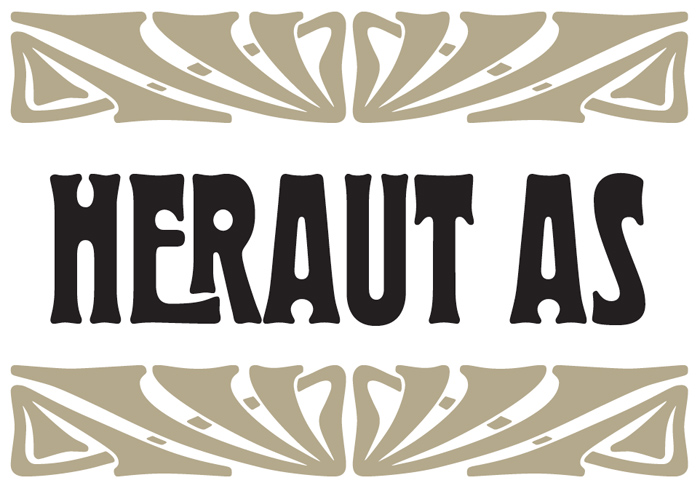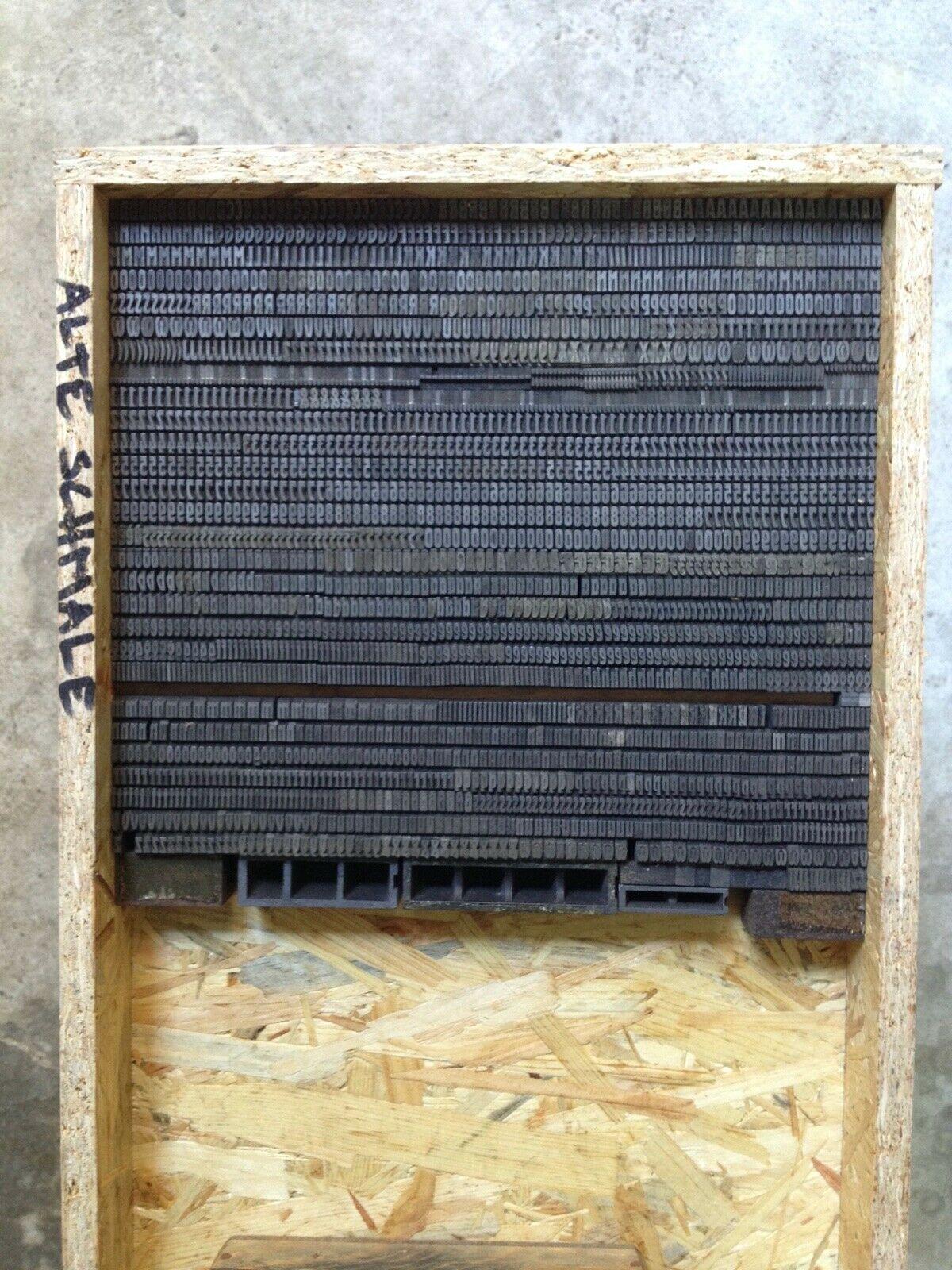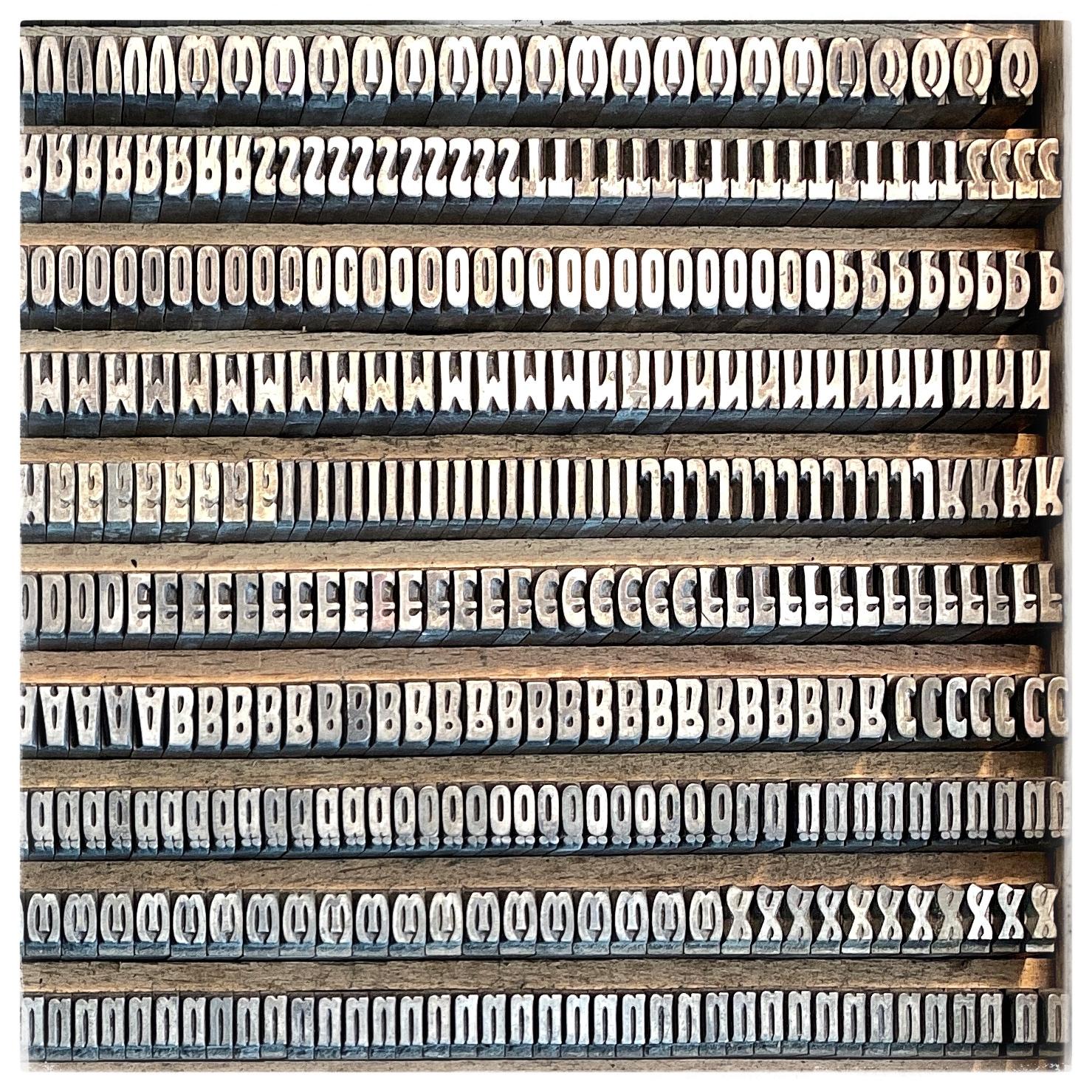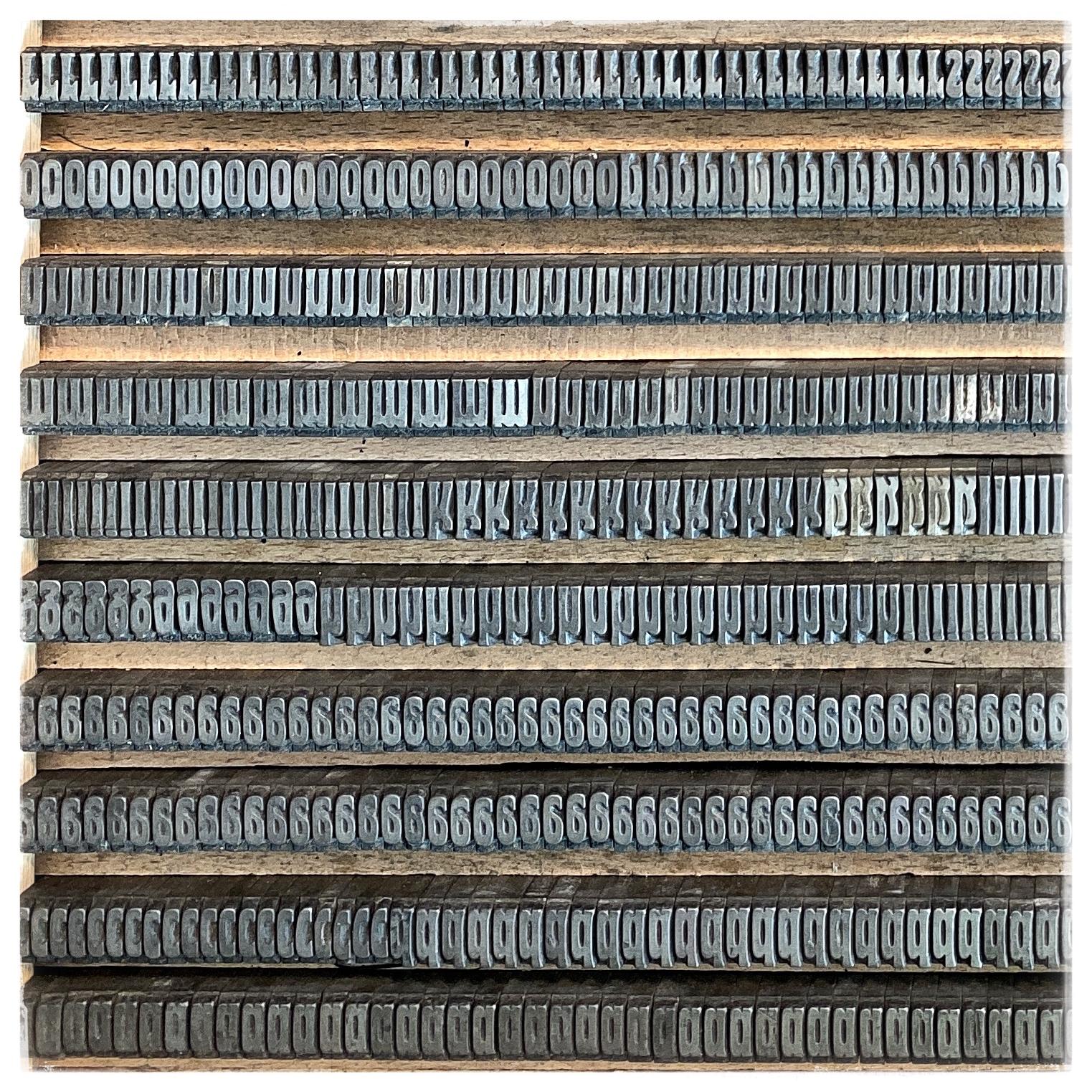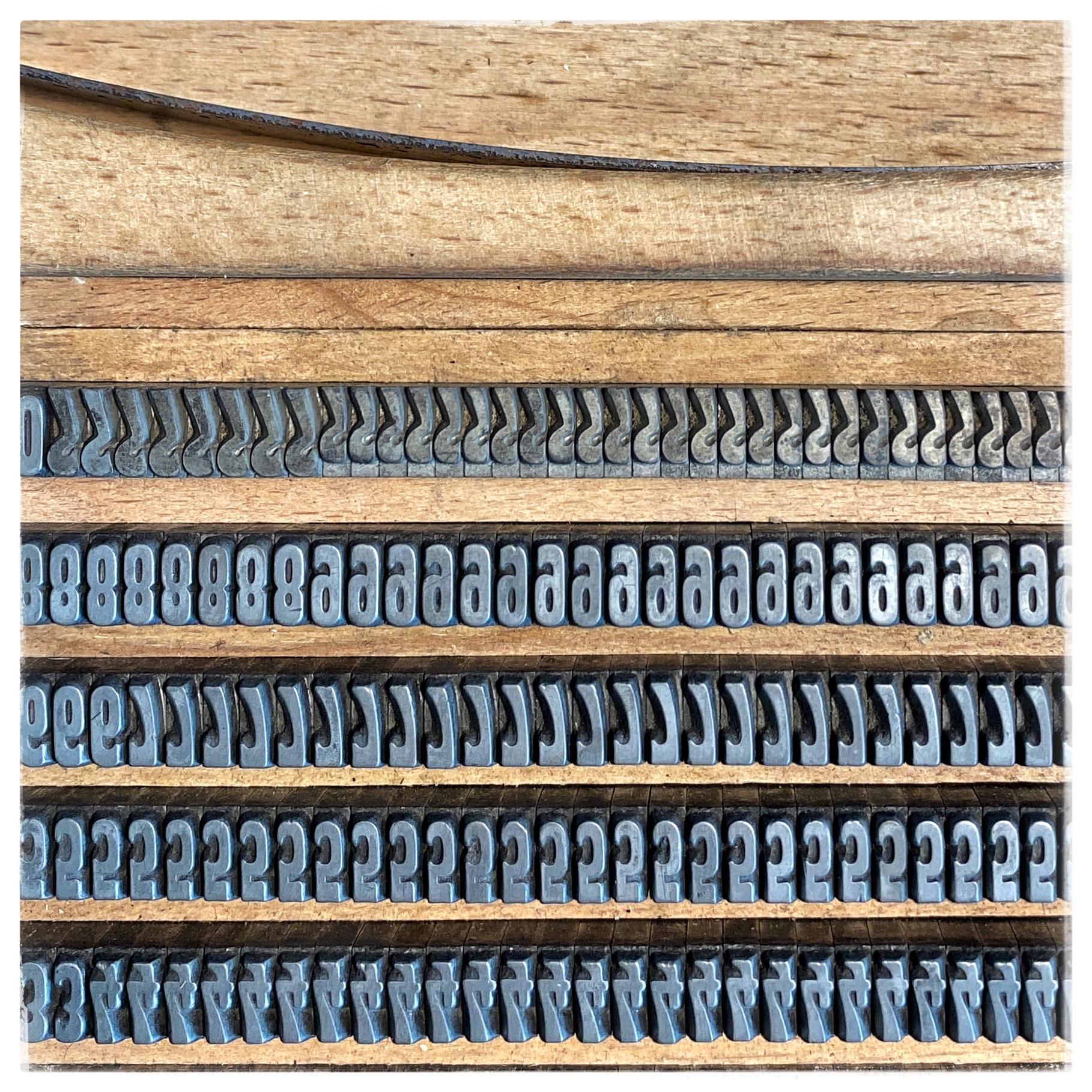
ich hab da wieder mal was erstanden … und weiss nicht so recht was!
Evt. kennt ja einer von euch diese Schrift.
Ja, es ist die Herold in 20 Punkt. Was ich bislang nicht wusste (da ich keine Schriftprobe zur Hand habe), dass die Schrift über so viele „Alternates“ verfügt. Im letzten Bild sieht man ein Zeichen, was mich etwas ratlos hinterlässt. Vielleicht habt ihr ja einen Tip was es sein kann.
Ich meine, dass das ein alternatives S bzw. ein Schluß-S ist. In meinen Heroldkästen waren diese Zeichen zumindest immer so einsortiert ... wie schön man das findet, ist ja jedem selbst überlassen.
Nachdem auf einer Seite ein glatter Abschluss ist – also kein „Fleisch“ an der Letter daran ist, könnte es sich um ein Anschluss- oder Abschlussteil für Linien handeln..
Vielleicht auch ein Eckstück für Rahmen, an dem Linien angeschlossen werden.
Könnte es, weil es hinter den Ziffern steht, ein Symbol für eine Maßeinheit sein?
War so etwas in zwei Höhen üblich?
Ich hab in meine Jugendstilschriftkästen geschaut. Solche Kringel finde ich nicht. Durchaus langes kleines s, auch großes S ohne und mit Unterlänge, aber keinen solchen Angelhaken. Kann man die Herkunft des Kastens ermitteln? Österreich, Schweiz, Belgien? Gibt es da Währungszeichen oder Zeichen für Maßeinheiten, die hier nicht in Gebrauch waren? Oder soll das eine Art Rune sein?
Ich schaue seit fast 40 Jahren in Setzkästen und hab das Zeichen noch nie gesehen, deshalb bin ich schon sehr wißbegierig.
Ich rate mal einfach ins Blaue hinein...
Auf der Typografie.info-Seite zur Herold ist ja dieses Bild hinterlegt:
Könnte es - ähnlich wie die „verstümmelten“ E und R Teil einer Ligatur sein?